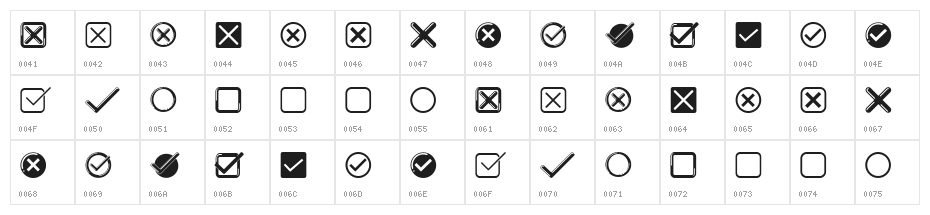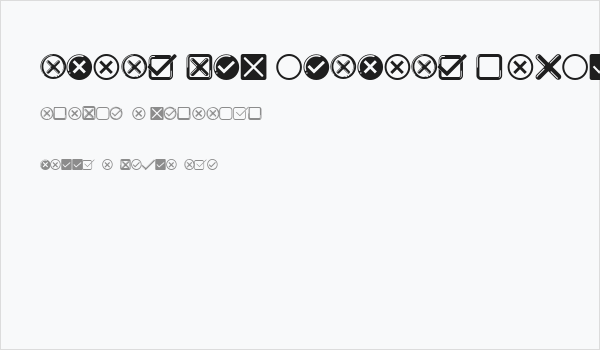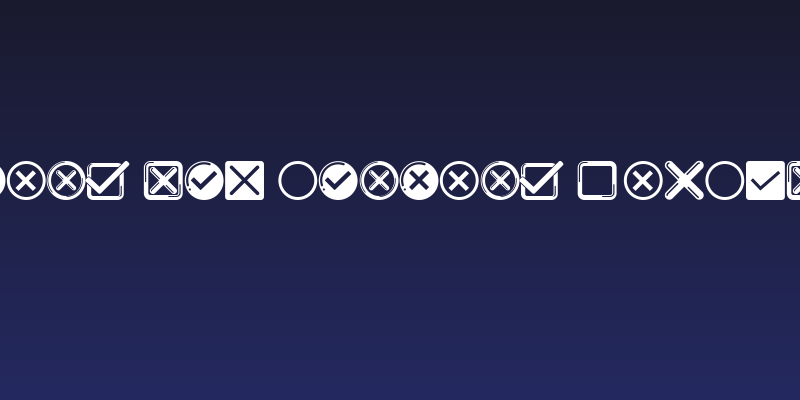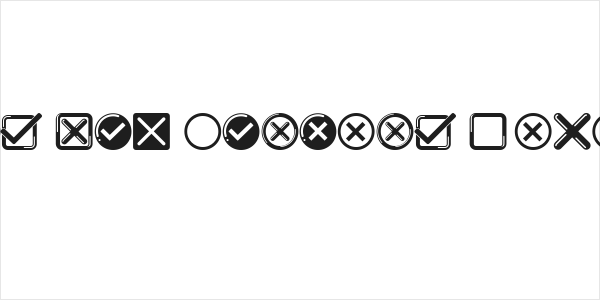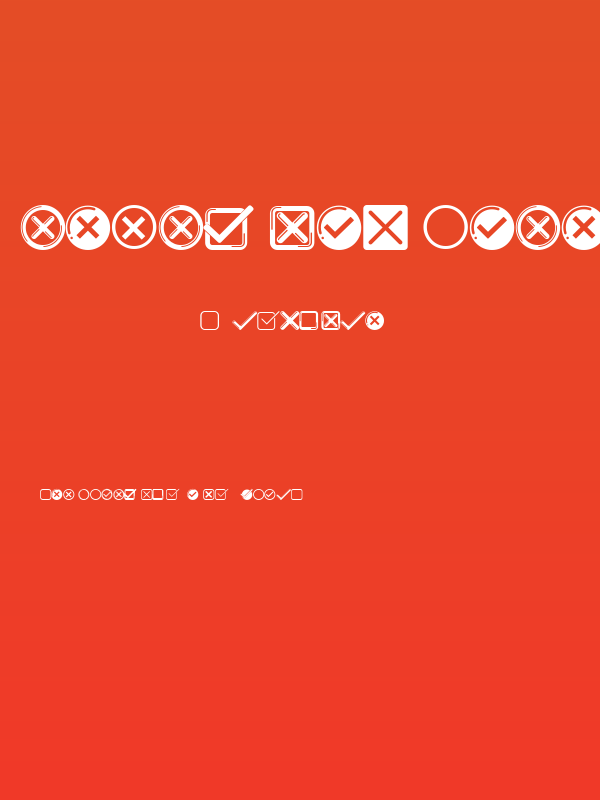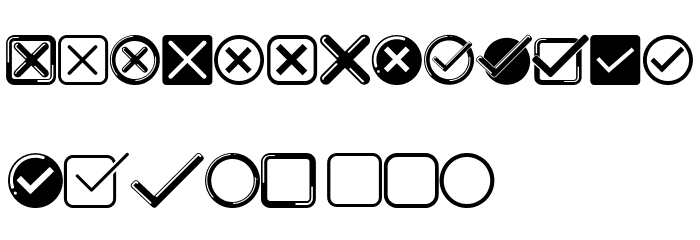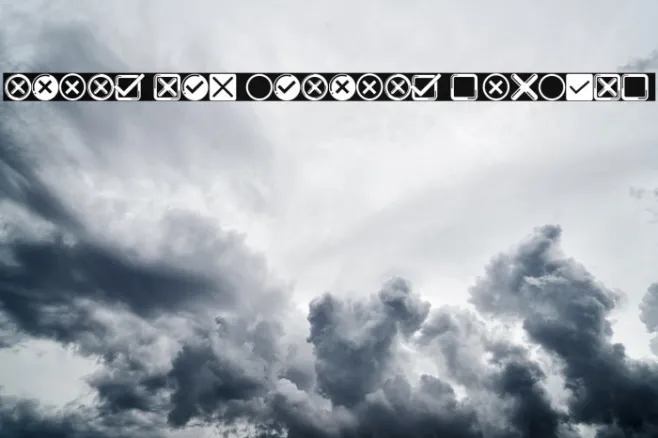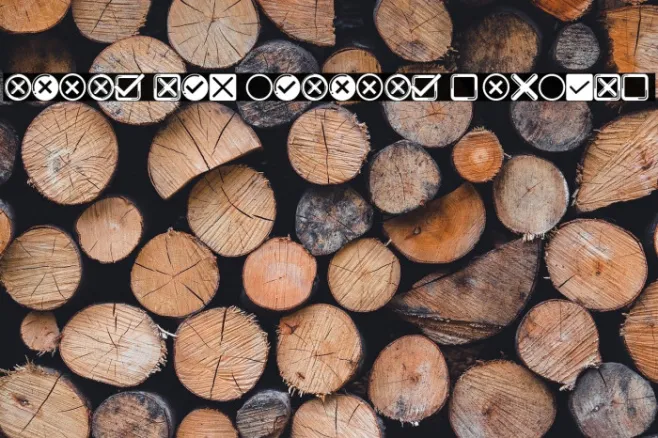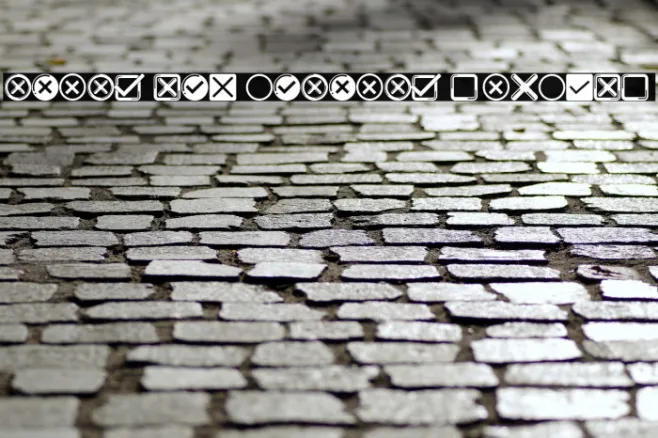
Check And Uncheck Regular Font
✎ Dingbats
| Anwendungsfall | Icons, User Interface |
| Vorgeschlagene Projekte | Ideal for user interface design, mobile apps, web applications, and any project requiring clear selection indicators. |